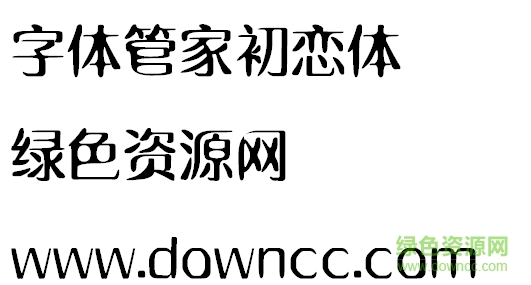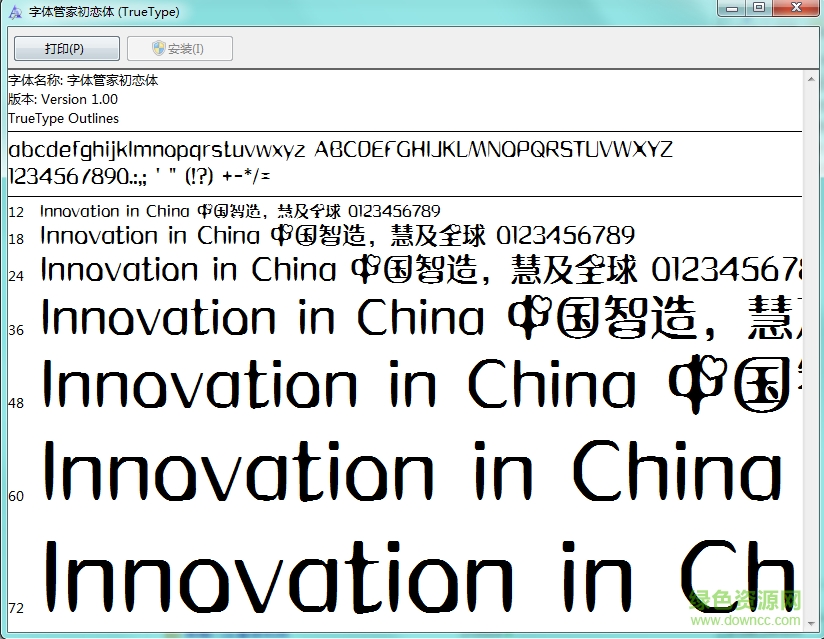
初戀體是字體管家推出的一款愛情藝術(shù)字體,充滿心形點綴,讓你感受怦然心動的初戀味道,字體簡潔清新,有著你喜歡的浪漫氣息,喜歡的朋友快來綠色資源網(wǎng)免費下載吧!
字體管家初戀體有著可愛圓潤的外觀,采用了心形圖案的修飾,讓字體充滿了戀愛的朦朦氣息,可適用于平面設(shè)計、廣告創(chuàng)意、藝術(shù)創(chuàng)作等領(lǐng)域,快來使用吧!